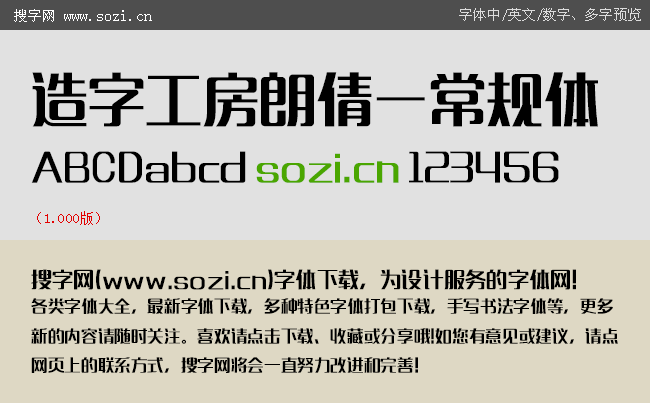
造字工房朗倩常規(guī)體(MFLangQian_Noncommercial-Regular)
搜字網(wǎng)提供一款造字工房朗倩常規(guī)體中文藝術(shù)字體下載,造字工房朗倩體共三款,筆畫簡(jiǎn)潔、粗細(xì)分明,中正不失圓潤(rùn),曲線流暢,結(jié)構(gòu)穩(wěn)重大方,整套字形柔和飽滿,如玉似珠,為漢字灌注了無(wú)限生機(jī)。整體字形姿態(tài)橫生,結(jié)構(gòu)疏朗飄逸,字里行間蘊(yùn)藏一種閑適沉靜之美。適合畫冊(cè)設(shè)計(jì),海報(bào)設(shè)計(jì),包裝設(shè)計(jì)等廣告設(shè)計(jì)場(chǎng)合使用。